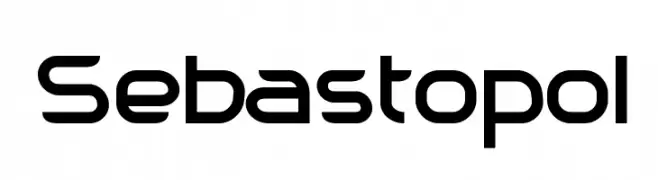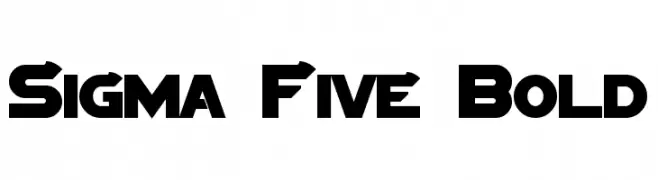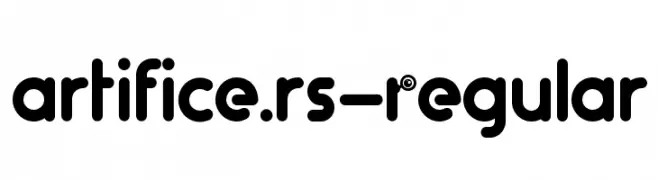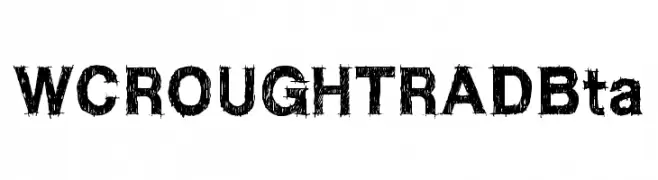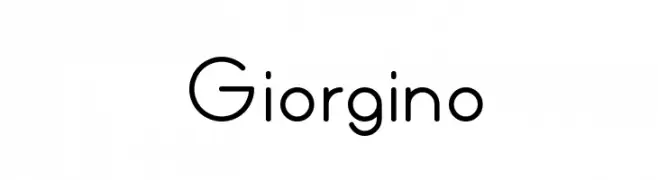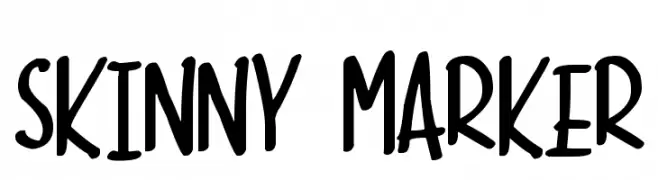
A modern, geometric sans-serif font with a futuristic and sleek design.
( Fonts by Robert A. Paauwe )
A playful, modern font with rounded edges and decorative elements.
( Fonts by Carrot Rope )
A bold, italic font with a dynamic slant and strong presence.
A dynamic, cursive script font with a personal and artistic touch.
A bold, graffiti-inspired font with dynamic, angular strokes.
( Fonts by Ingo Zimmermann - www.ingofonts.com )
A bold, modern font with thick, uniform strokes for strong visual impact.
( Fonts by Christophe Feray - www.wcfonts.com )
A rugged, distressed font with a bold, gritty aesthetic.
( Fonts by Have Fun with Fonts )
A bold, condensed font with an Art Deco style and high contrast strokes.
( Fonts by Davide Ardissone )
A modern, geometric font with clean lines and uniform stroke width.
Дизайнеры любят Sebastopol, Sigma Five Bold, artifice.rs-Regular, Newside FP Italic and OPTIChampion-Script за чистые формы и широкий спектр применения — от фирменного стиля до лендингов и постеров.